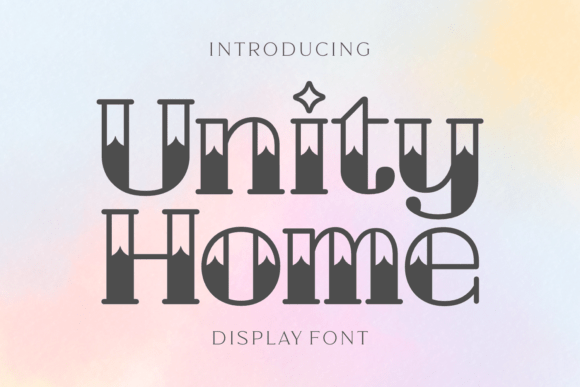
Unity Home
หากคุณกำลังมองหาเนื้อหาคุณภาพสูงเช่น Unity Home แพ็คเกจพรีเมียมนี้เป็นตัวเลือกที่ยอดเยี่ยมสำหรับโปรเจ็กต์สร้างสรรค์ของคุณ
สร้างขึ้นอย่างแม่นยำ Unity Home ให้เวกเตอร์ที่สะอาด พิมพ์ตัวอักษรที่ราบรื่น และใบอนุญาตเชิงพาณิชย์เพื่อความสบายใจ